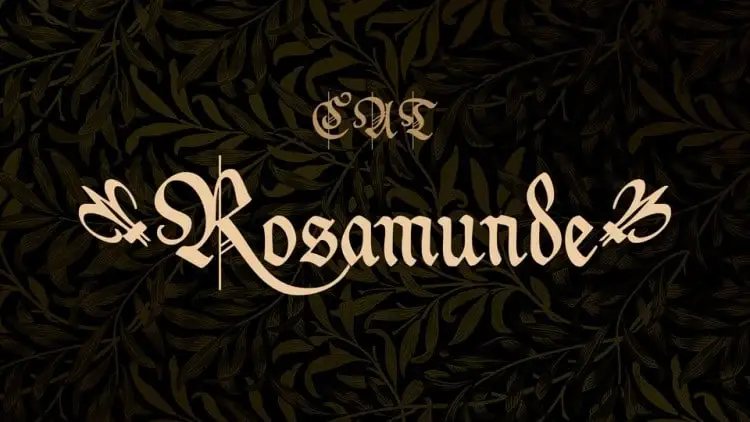
A Rosamunde Display Font é uma escolha perfeita para quem busca expressar elegância e audacia através do design tipográfico. Fabricada pelo designer Peter Wiegel, essa fonte em estilo Blackletter traz os atributos góticos, proporcionando um ar refinado e sofisticado. O seu formato inclui terminais macios, curvas sedutoras, uma graça chamigrafica e complexidade nos caracteres, formando uma combinação poderosa de elegância e desafio que vai revolucionar sua identidade visual. Perfecto para criar um design que chama atenção e transmite paixão, seja num site web atraente ou em materiais impressos memoráveis. Experimente e descubra porque esta fonte é uma escolha indispensável para qualquer designer gráfico.